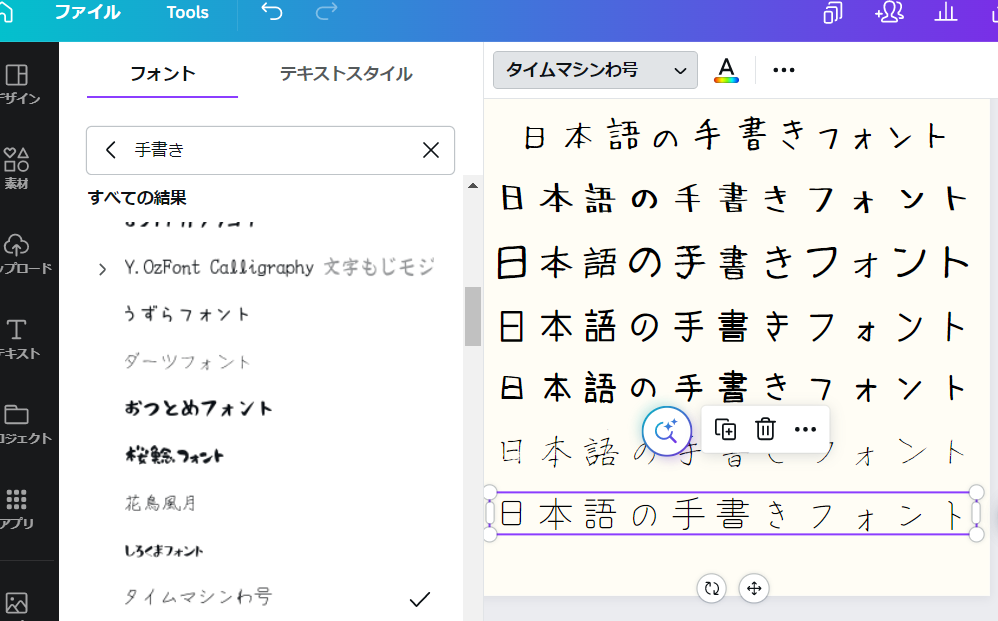
日本語の手書きフォントには可愛いスタイルがいっぱい。ペン字、マジック、じゆうちょうフォント、細ペンのフォントがおすすめ!線が細いものから太いものまで、丸みのあるフォントから角張ったフォントまで、多種多様に取り揃えております。インスタ投稿、写真アルバム、ハガキ、メッセージカード、動画、リール、チラシ、ポスター、ステッカー、トートバッグなど、どんなデザインにも使用できます。
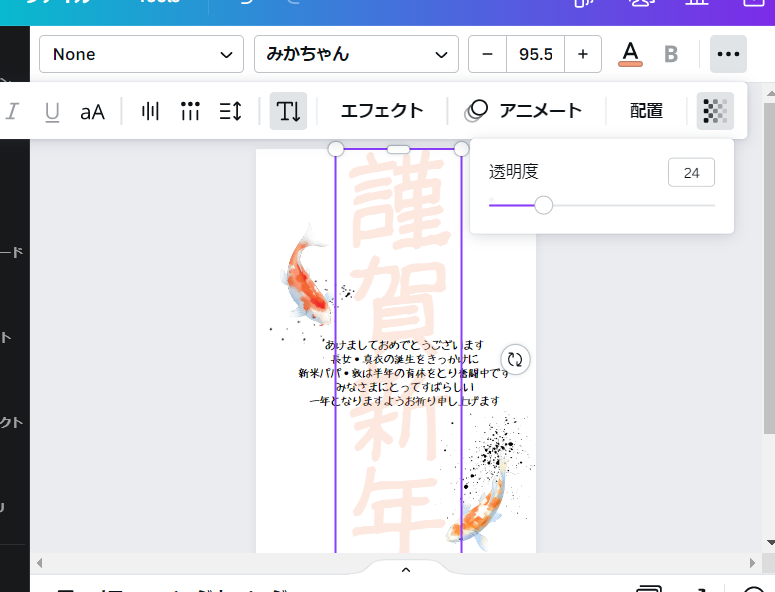
日本語の手書きフォントで文字を大きく書いてデザインの背景に配置するのもおしゃれ。メッセージカードやはがき、年賀状のデザインにも使えるテクニックです。文字を配置したら、カラーを変えて用紙いっぱいに大きく広げましょう。必要なら透明度も使って、背景っぽくやわらかいタッチを加えましょう。さいごに、文字の上をクリックして最背面に設定したら、完成!前面にメッセージを書いたり、本文テキストを書いたらデザインの出来上がり!
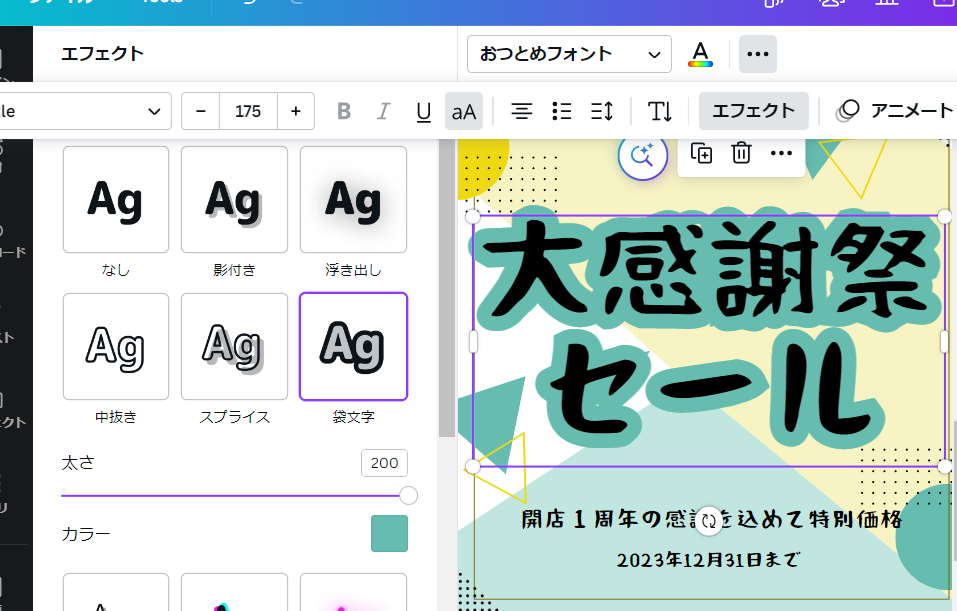
文字を選択した後、上部のメニューバーから[エフェクト]を押します。左画面に様々なエフェクト機能が表示されます。「袋文字」を選択してテキストカラーを選択しましょう。フチの部分は太さが変えられる上、文字は平行だけでなく湾曲にしてカーブさせることも可能です。袋文字を使用すれば、POP広告の作成やインスタ広告にもぴったりなデザインが作成できます。
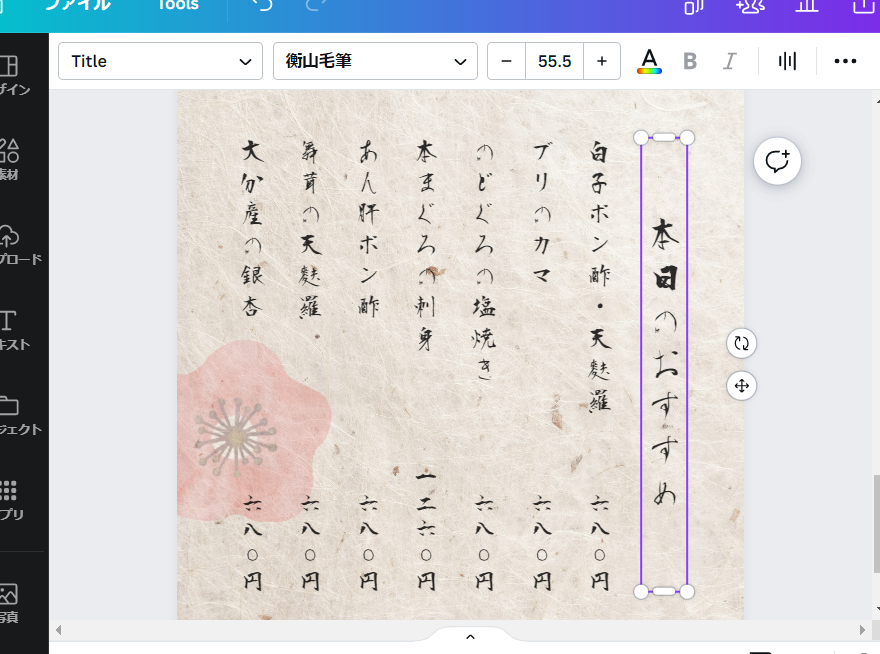
日本語の手書きフォントもかわいいですが、毛筆フォントは雰囲気を出せる素敵なフォントです。居酒屋や和食レストランのメニューにおすすめです。[テキスト]の検索バーに「筆」と入力すると、あらゆる筆フォントが表示されます。力強い毛筆フォントから繊細で優しい雰囲気を出せる毛筆フォントまで、数多くの種類から選ぶことができます。